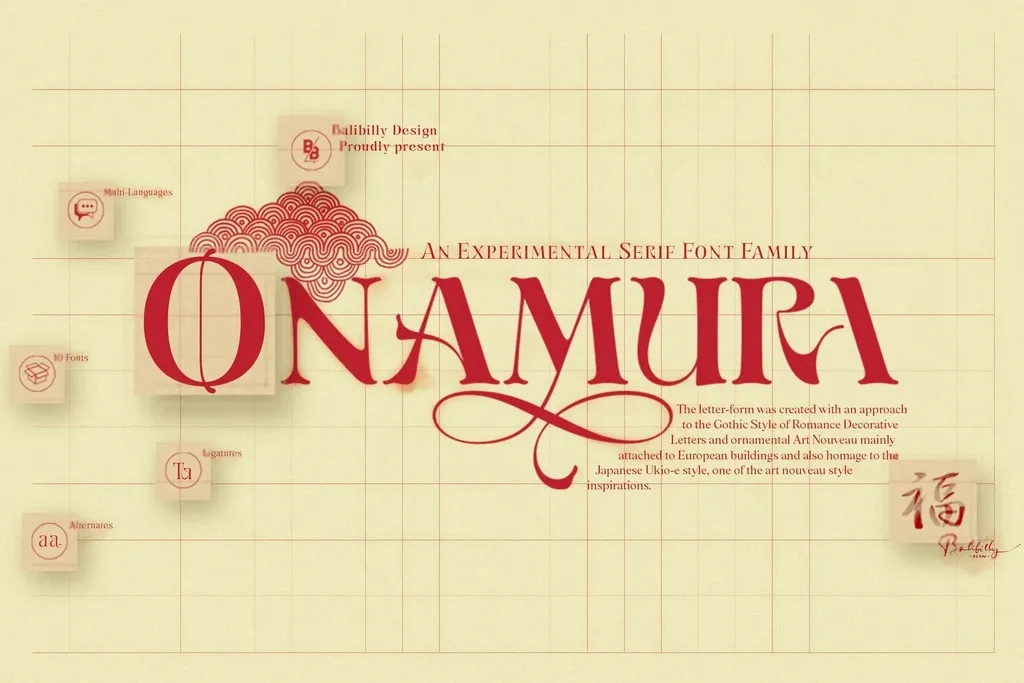
Onamura Font
A fonte ‘Onamura Font’ é um belíssimo exemplar do gênero Display Fonts, criado por Balibilly Design para a categoria de tipografias vintage e sofisticadas. Inspirada nos estilos serifados do Renascimento, essa fonte transmite uma atmosfera elegante e retrô que combina elementos modernos em harmonia com suas origens. Através da evolução art nouveau, foi desenvolvida para capturar o espírito do século XX, oferecendo linhas dinâmicas e curvas atraentes que refletem os movimentos arquitetônicos e gráficos da época. Seu design moderno, embasado no digitalizado de suas referências art-nouveau, também é chamado de estilo psicodélico. Essa combinação faz com que ‘Onamura Font’ seja uma escolha perfeita para uso em logotipos e design gráfico, adicionando um toque único e moderno a qualquer projeto. Esteve inspirado nos estilos tradicionais da arte renascentista e modernizou-se de maneira interessante para atender às necessidades de um design visual contemporâneo. O resultado final é uma fonte que transmite elegância, sofisticação e modernidade, tornando-se uma escolha inteligente para quem procura uma combinação única de estilos passados e futuristas.